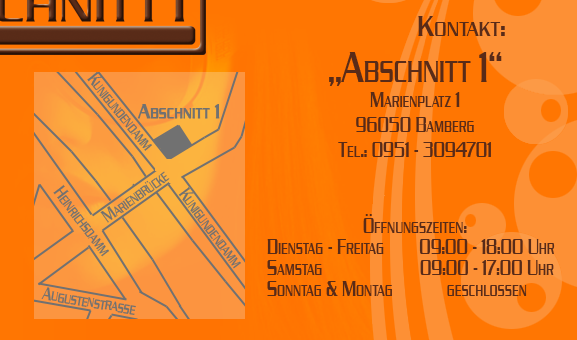
Suche Schriftart eines alten Auftrags
ich suche die Schriftart, mit der sowohl das folgende Logo, als auch die Webseite gestaltet wurde.
Die Schrift wird nur in Großbuchstaben verwendet. Markant ist das "C", das sehr eckig erscheint. Im Gegensatz zu Arial besitzt die Schriftart auch feine Serifen.
Ich habe Logo und Seite vor einigen Jahren selbst gestaltet, finde die Schriftart aber leider nicht mehr auf meinen aktuellen Systemen.
Vielleicht Adobe Serpentine Std ?
Ich kann leider nicht helfen, habe aber ein Bitte: Vermeidet bei der neuen Version bitte dieses fürchterliche ß!
Am besten solltet ihr generell eine bessere Schrift benutzen, die – wenn eine möglichst ähnliche Anmutung sein muss – über echte Kapitälchen und idealerweise eben auch ein Kapitälchen-ẞ verfügt.
Lässt sich keine Schrift mit ẞ finden, schreibt AUSSCHLIESSLICH, GRÖSSER etc. – oder besser gleich Gemischtsatz.